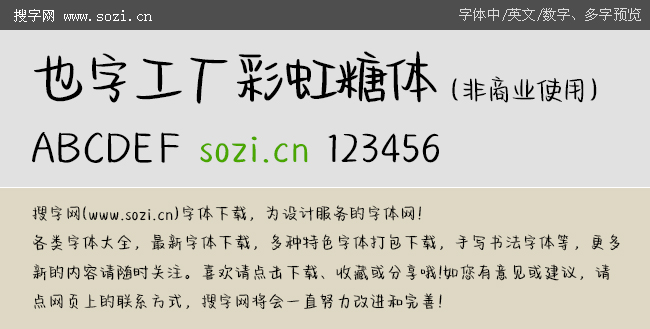
也字工廠彩虹糖體
搜字網(wǎng)給大家提供一款也字工廠彩虹糖體(非商業(yè)使用)中文字體下載,也字工廠彩虹糖體是一款手寫風(fēng)格的卡通字體,字體書寫富于變化,字形帶有趣味性。具有很好的視覺效果。適合應(yīng)用于藝術(shù)設(shè)計(jì)、平面宣傳設(shè)計(jì)、網(wǎng)頁設(shè)計(jì)、海報(bào)設(shè)計(jì)等應(yīng)用(此字體為個(gè)人非商用版,商用可以聯(lián)系:官方網(wǎng)址:https://yefont.com/home,聯(lián)系方式:13798980448)。